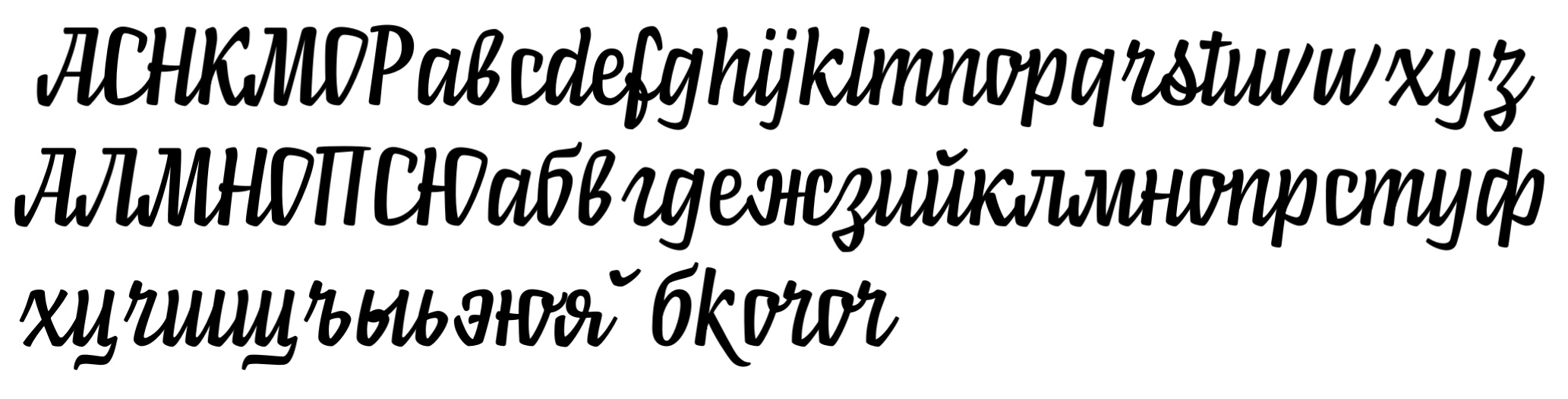
Рукописный
2026-08-15 – Вчера нарисовал леттеринг, пара строк из которого навела меня на мысль сделать такой рукописный.
Делал весь день, аж тошно стало. Но надеюсь скоро применить его в одном деле.